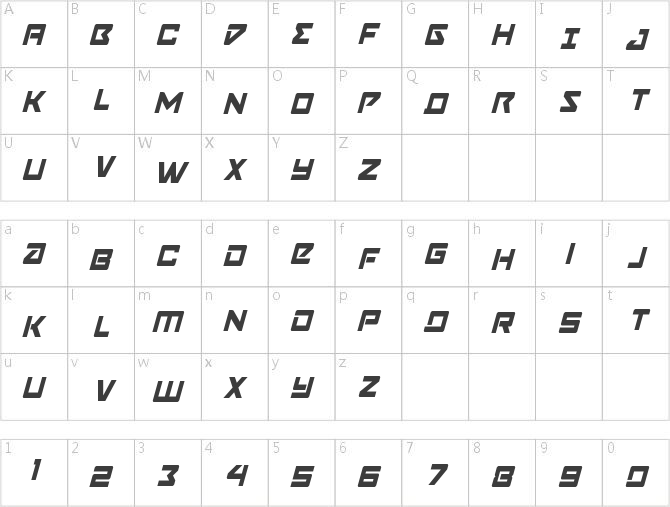
Navy Cadet Condensed Italic 詳情頁(yè)
Navy Cadet Condensed Italic字體字庫(kù)是一款讓人賞心悅目、百看不厭的英文字體,適合各類廣告和產(chǎn)品包裝設(shè)計(jì)應(yīng)用,字體大小0.03MB,格式為ttf字體,上傳用戶是細(xì)雪無(wú)聲,作者/版權(quán)方為未知